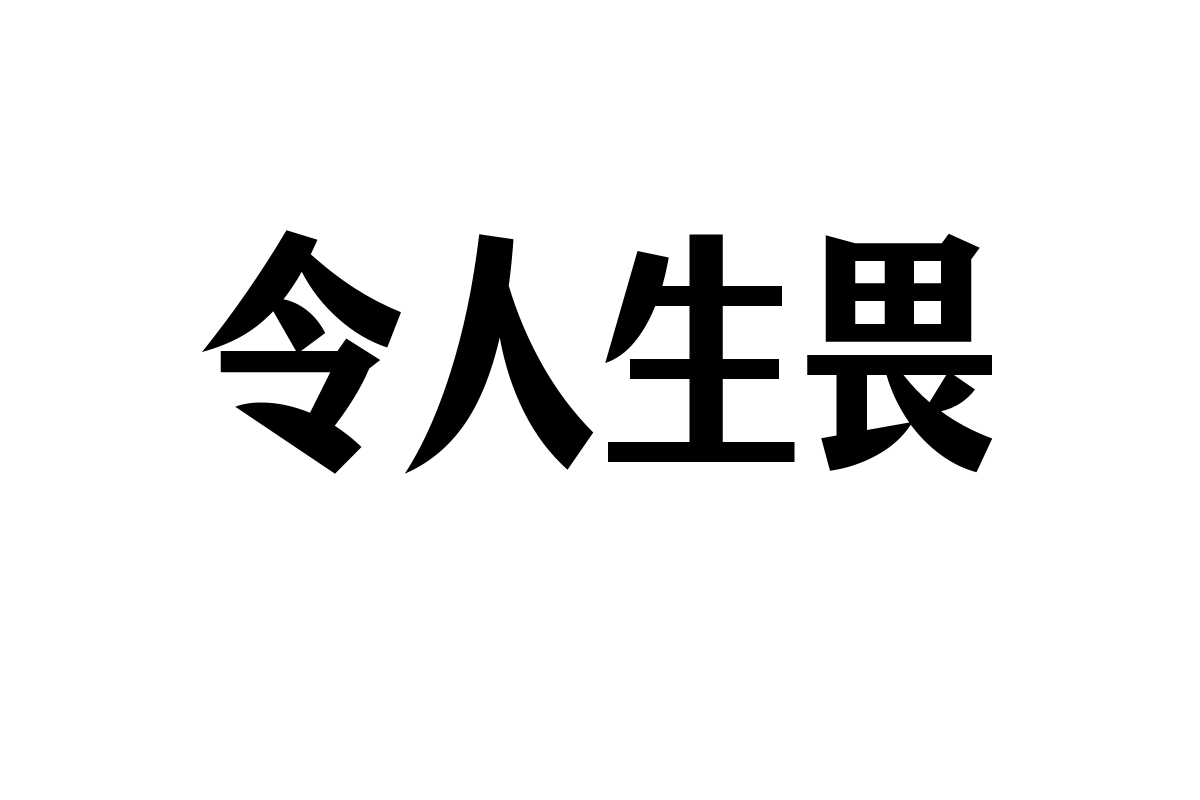
仓耳启明体是一款现代中文字体,由上海仓耳信息科技有限公司设计。这款字体具有独特的风格和特点,适合用于需要清晰易读的文本展示,如标题、副标题、广告、标志等。
仓耳启明体的笔画粗细适中,线条流畅自然,给人一种简洁而有力的视觉感受。它的字形结构紧凑,但不失优雅,能够很好地适应各种排版需求。同时,该字体还注重细节的处理,如字间距、行间距等,使得整体效果更加协调统一。
总的来说,仓耳启明体是一款非常适合现代商业和办公环境的中文字体,无论是在印刷还是电子媒体上都能展现出其独特的魅力。